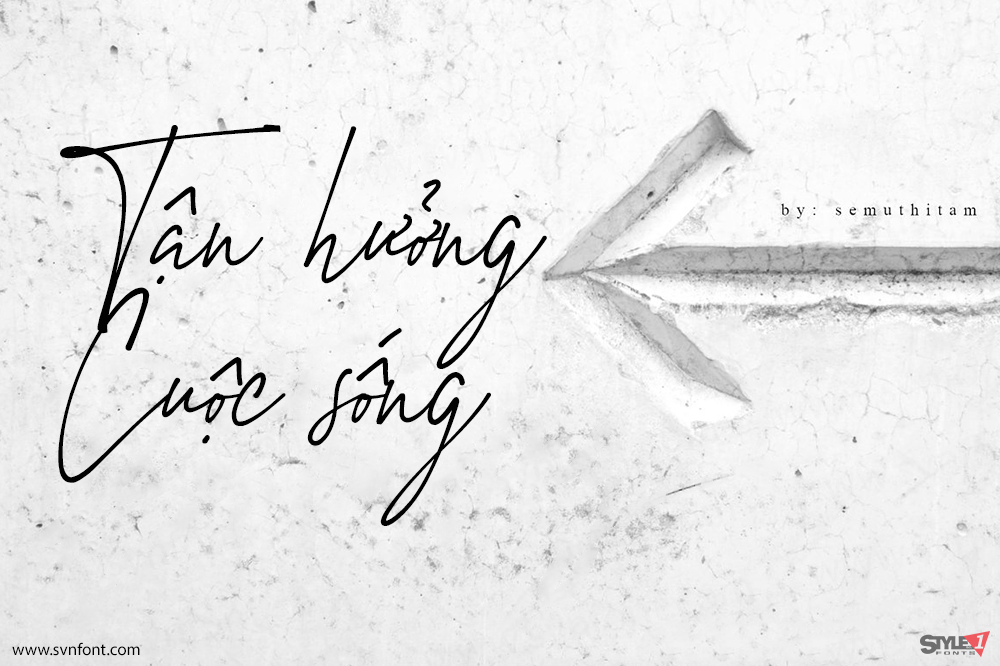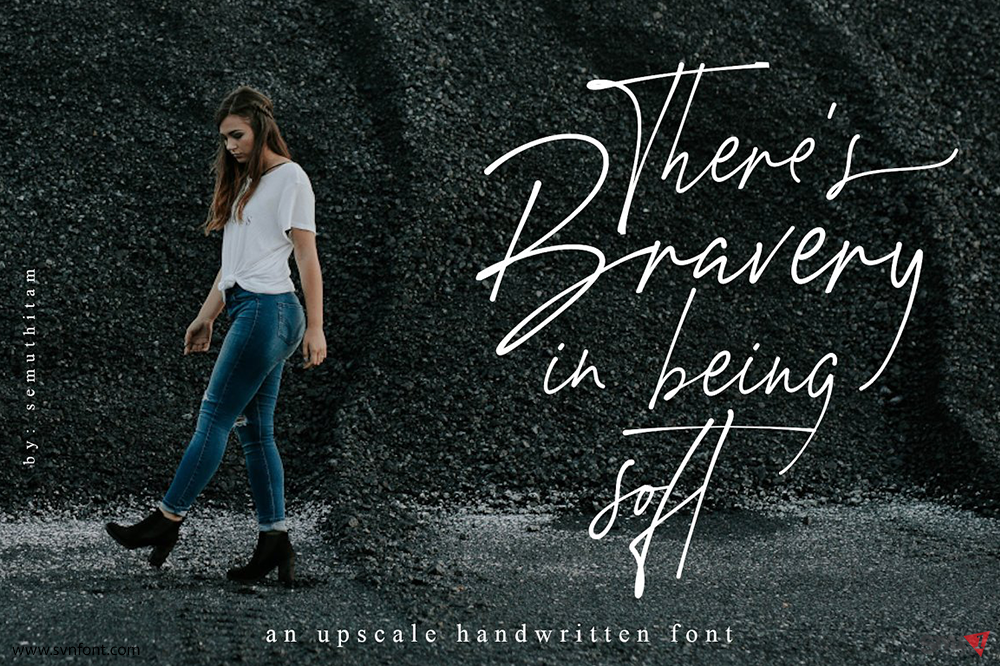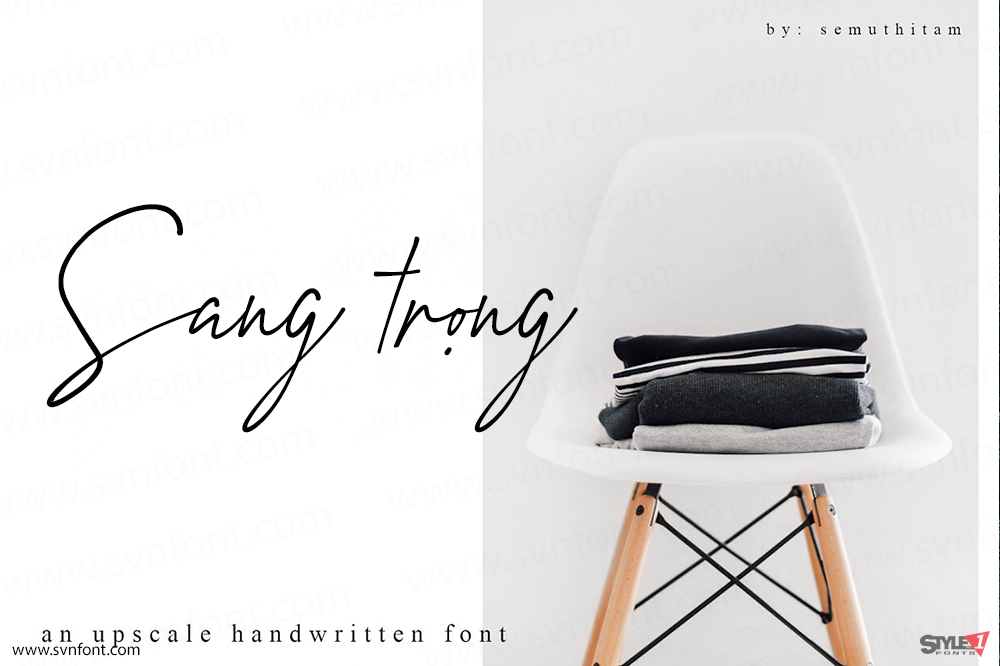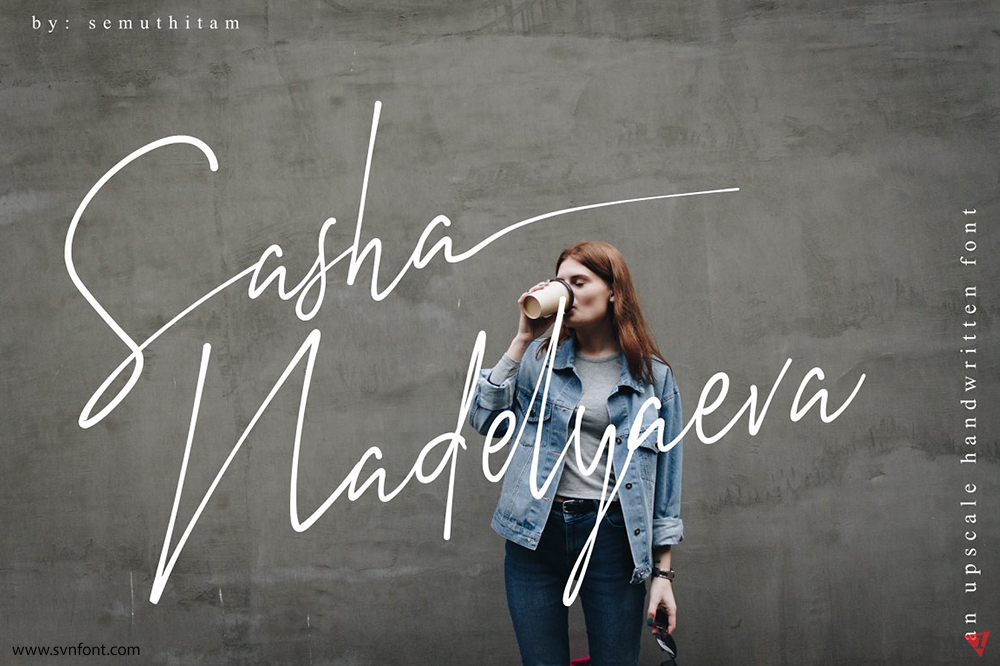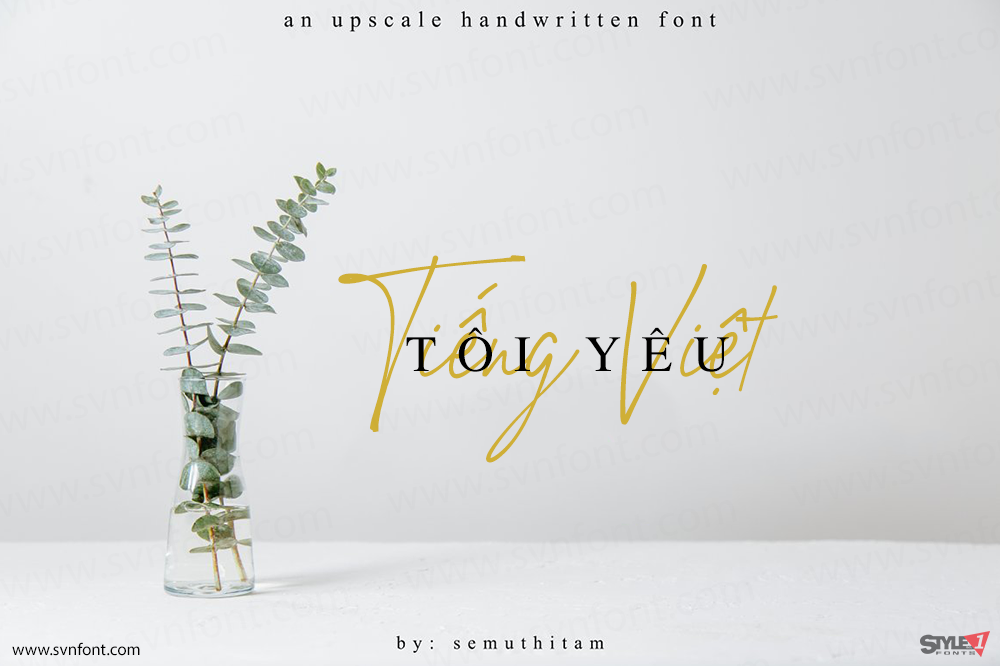
Amstirdam là một font script viết tay cao cấp, rất phù hợp cho nhu cầu branding, thiệp cưới, danh thiếp và nhiều ấn phẩm in ấn khác.
Font bao gồm đầy đủ chữ hoa, chữ thường thanh lịch, chữ số, dấu câu, hỗ trợ đa ngôn ngữ cùng nhiều ligature. Đặc biệt, mỗi chữ thường có 2 biến thể nét kết, giúp tạo cảm giác chữ viết tay chân thực và tự nhiên cho thiết kế của bạn.